Шрифты в Фотошопе: как выбрать идеальную печатную поддержку для вашего дизайна
Выбор подходящего шрифта для дизайна в Фотошопе – важный этап, от которого зависит эстетическая и практическая составляющая проекта. Здесь вы найдете полезные советы и идеи для выбора и настройки шрифта, чтобы сделать ваш дизайн неповторимым и уникальным.
Исследуйте различные типы шрифтов и их эффекты на дизайн. Попробуйте санс-сериф, сериф, курсивные, рукописные шрифты и другие стили, чтобы найти подходящий для вашего проекта.
Учитывайте контекст и цель вашего дизайна. Некоторые шрифты могут подходить для заголовков и выделения ключевых элементов, а другие лучше подойдут для длинных текстовых блоков.
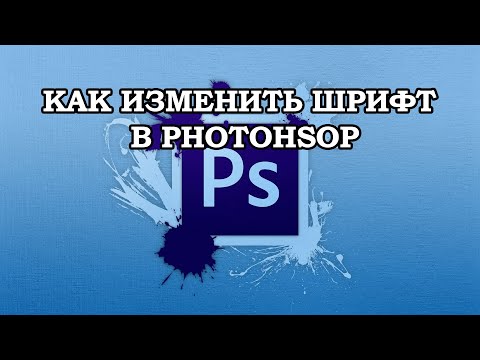
Играйте с размером и интерлиньяжем шрифта, чтобы достичь оптимальной читаемости и визуального воздействия. Увеличение межсимвольного расстояния может помочь улучшить читаемость шрифта.